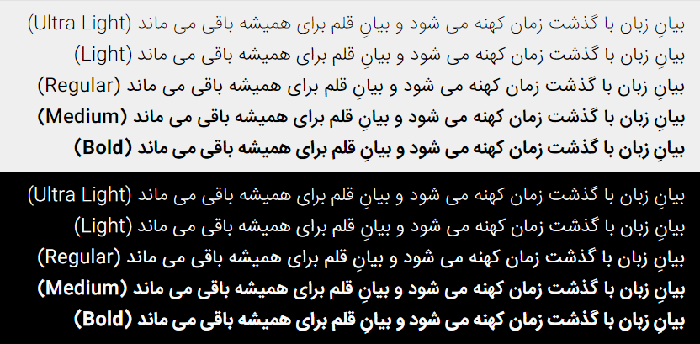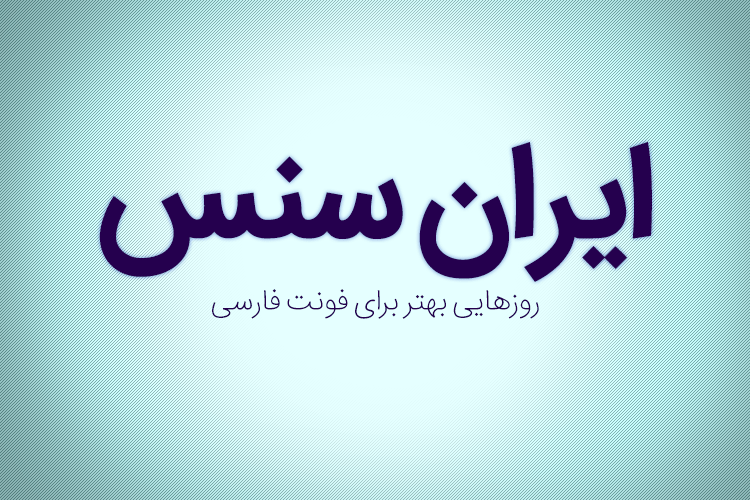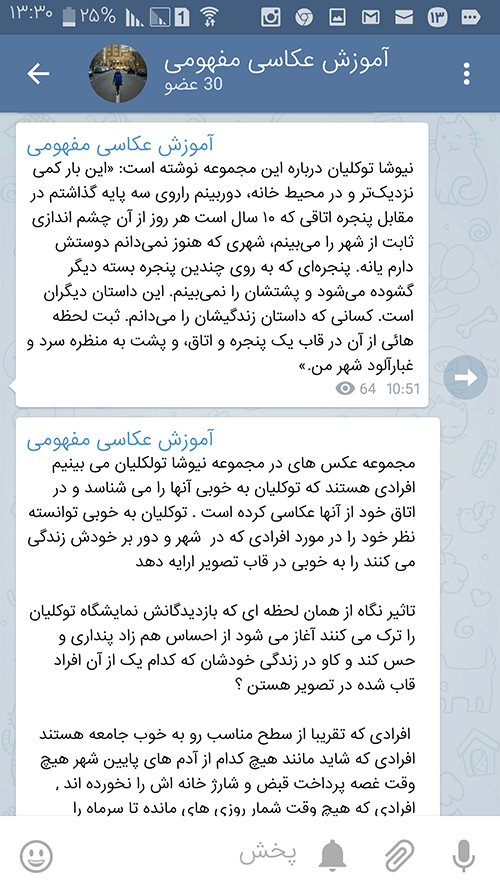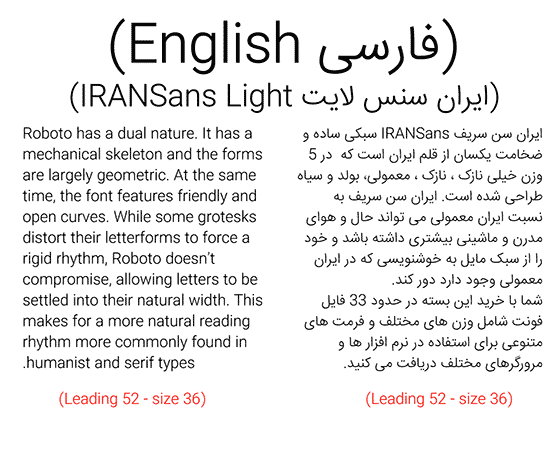
این فونت که توسط مسلم ابراهیمی طراحی شده و در تابستان ۱۳۹۴ توسط سایت fontiran.com فروش آن آغاز شد، در مدت کوتاهی توانست در زمینه طراحی وب و نرم افزار آنچنان فراگیر شود که هم اکنون بسیاری از سایتها و نرم افزارهای معروف ایرانی مانند دیجیکالا – کافه بازار – ایرانسل - آپارات - میهن بلاگ و ... از آن استفاده میکنند.
در این مطلب قصد داریم دلایل فراگیر شدن این فونت و البته در کنار آن محدودیتهای استفاده از آن را توضیح دهیم.
به چه دلیل فونت ایران سنس پرطرفدار است:
۱- این فونت واقعاً خوانا و واضح است. کمتر فونت فارسی در سایز خیلی ریز (بخصوص در نرم افزارهای موبایل میتواند به وضوح ایران سنس دیده شود)
۲- این مجموعه فونت شامل 5 وزن است. همه ما دیدهایم که فونتهای لاتین معمولا در وزنهای متنوعی طراحی میشوند. اما درباره فونت فارسی شاید این اولین فونتی باشد که دارای وزنهای خیلی نازک، نازک، معمولی، متوسط و بولد است. این تنوع امکانات زیادی را هنگام طراحی در اختیار شما قرار میدهد.
اما استفاده از این مجموعه فونت محدودیتهایی هم دارد:
اما با این حال ظهور چنین مجموعه فونتی با همه مزایا و محدودیتها قدمی رو به جلو برای فونت فارسی در ایران محسوب میشود. شاید این شروع یک جریان برای قطع وابستگی ما فارسی زبانها به فونتهای نه چندان زیبای ویندوز، اپل و گوگل باشد.
به امید روزهایی بهتر برای فونت فارسی